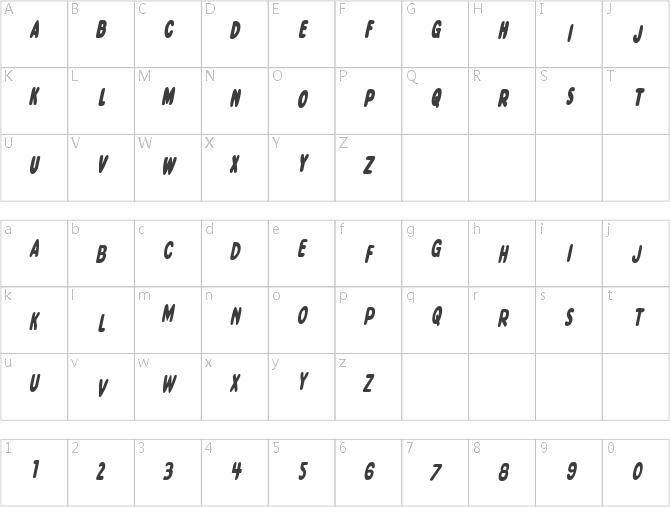
excelsiorcomicscondital 詳情頁
excelsiorcomicscondital
excelsiorcomicscondital字體字庫是一款讓人賞心悅目、百看不厭的英文字體,適合各類廣告和產品包裝設計應用,字體大小0.05MB,格式為ttf字體,上傳用戶是我,Dirac,作者/版權方為未知